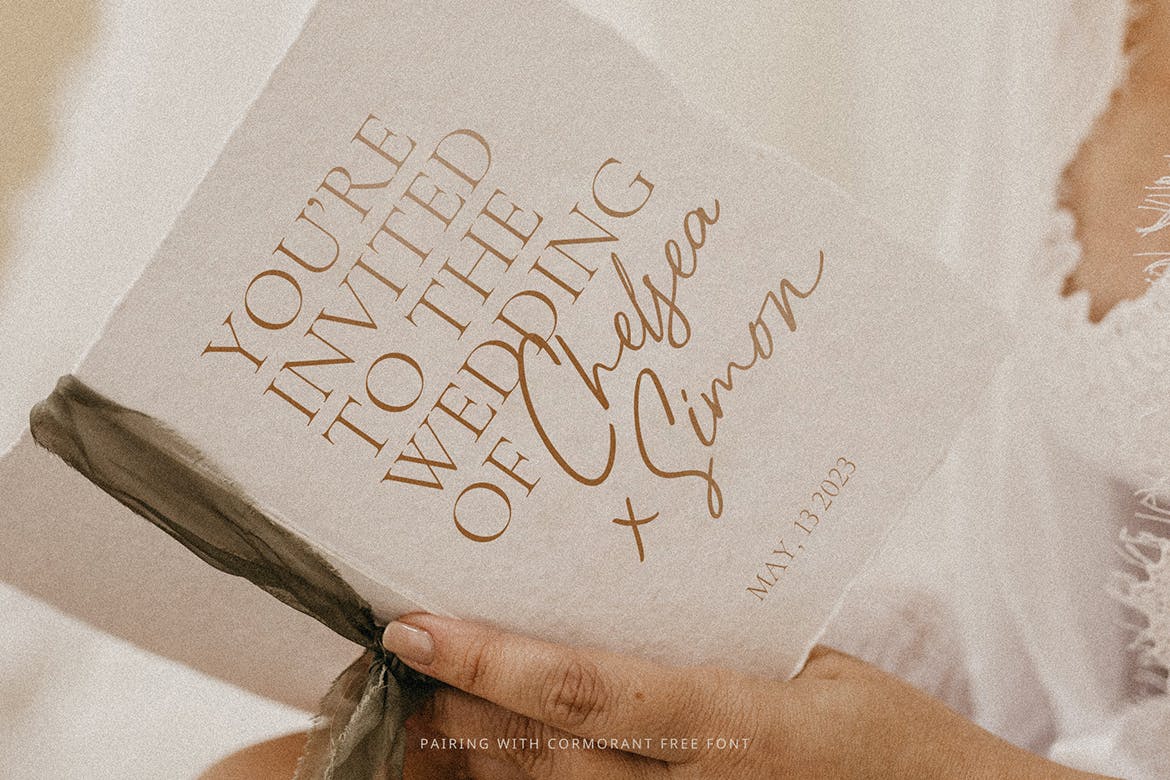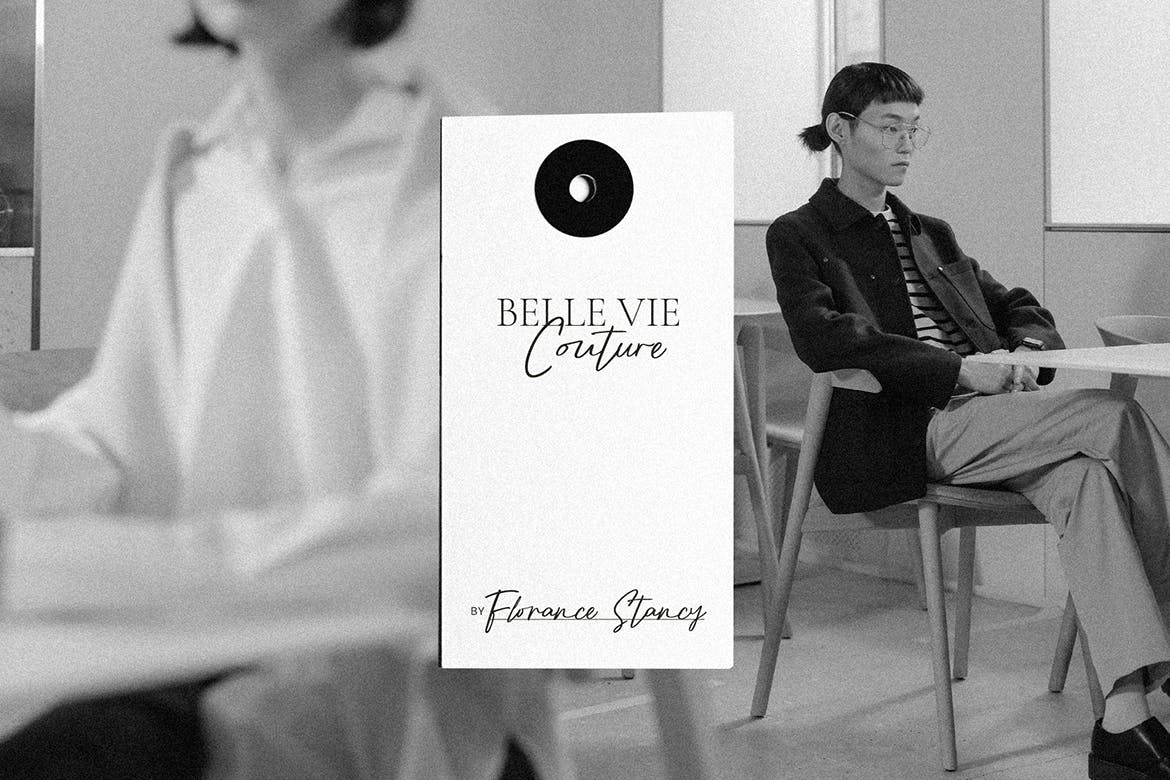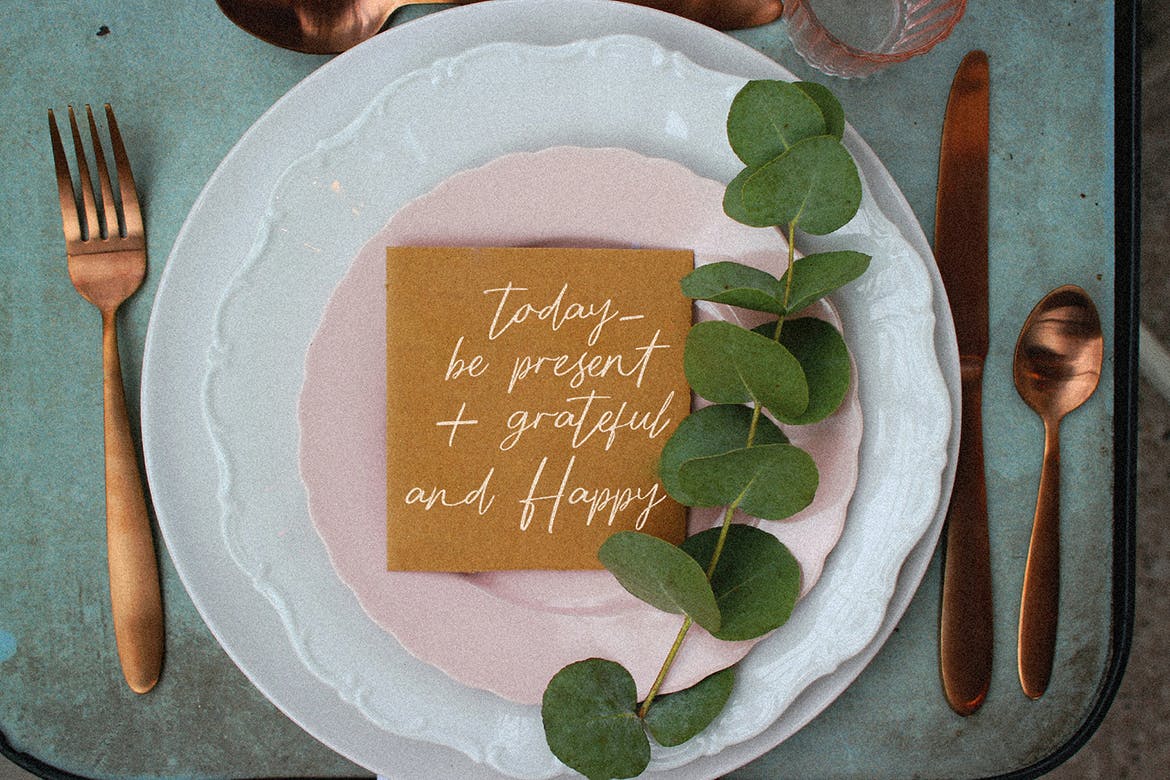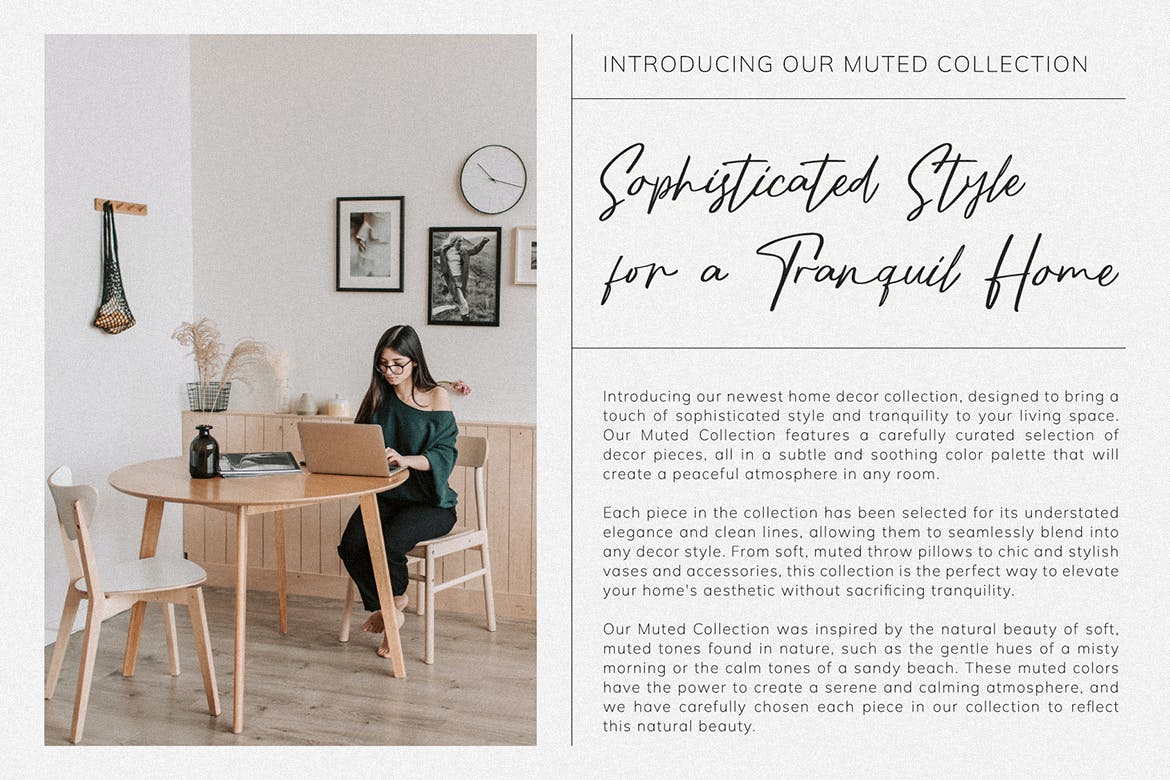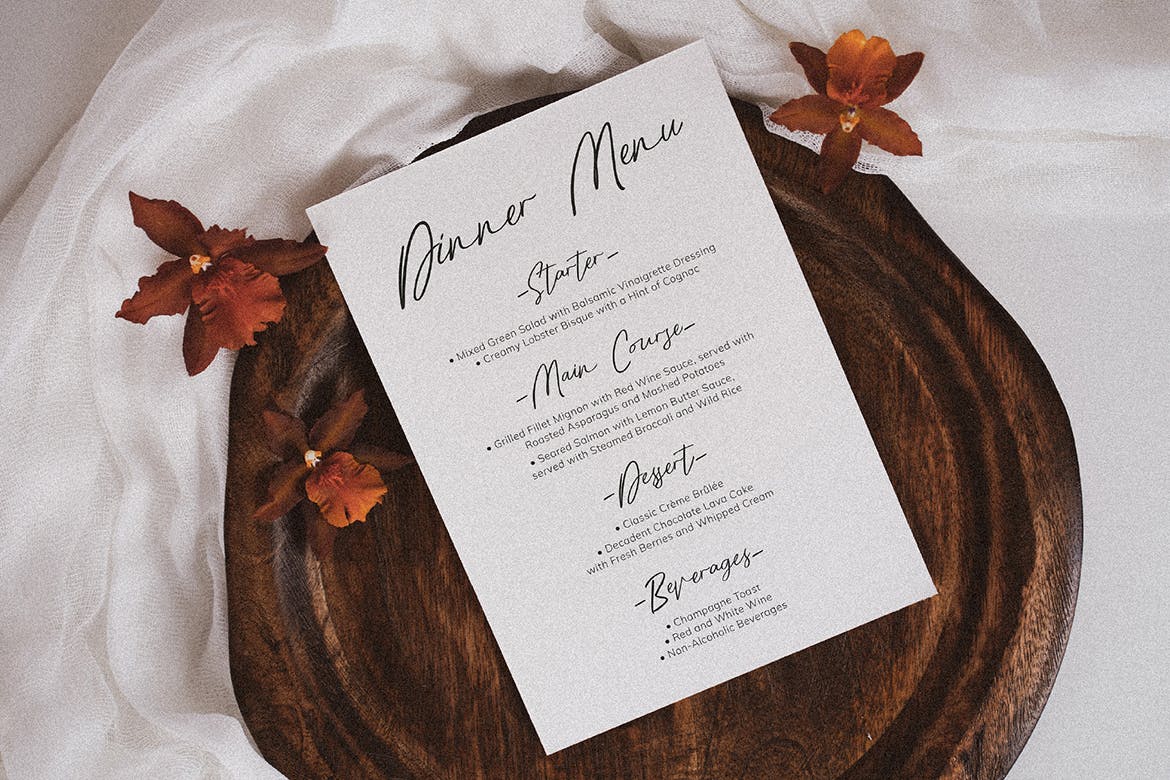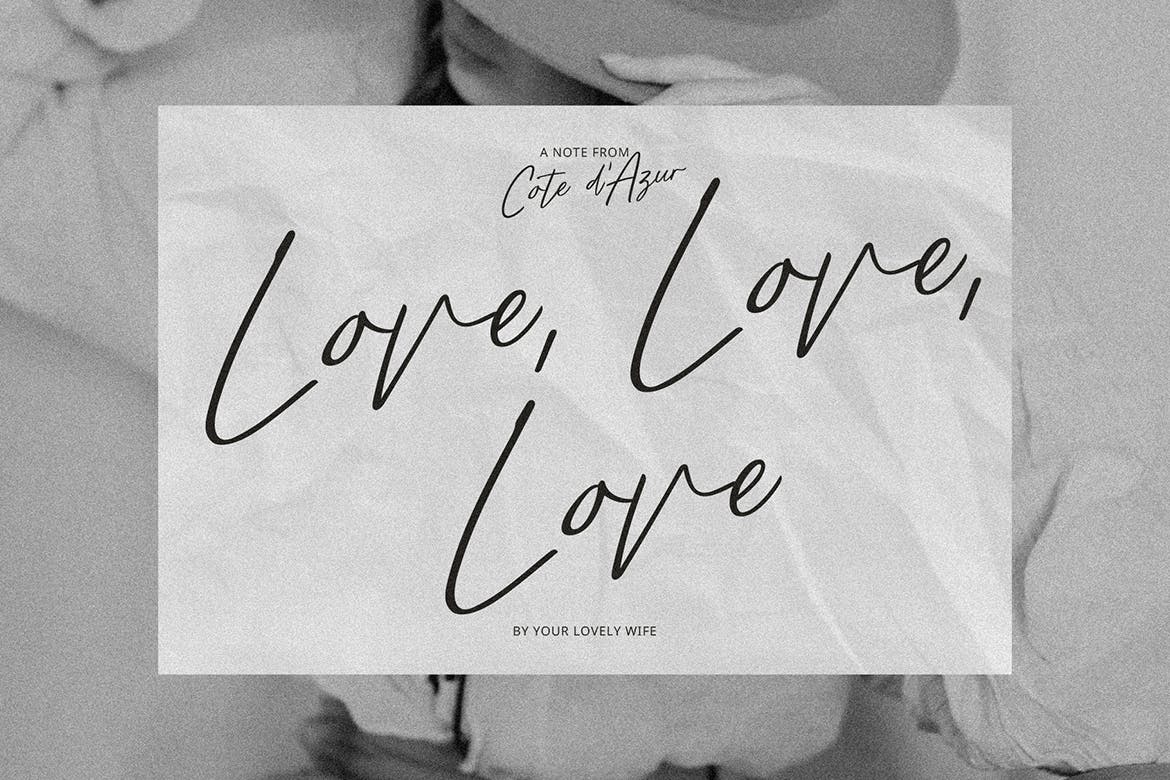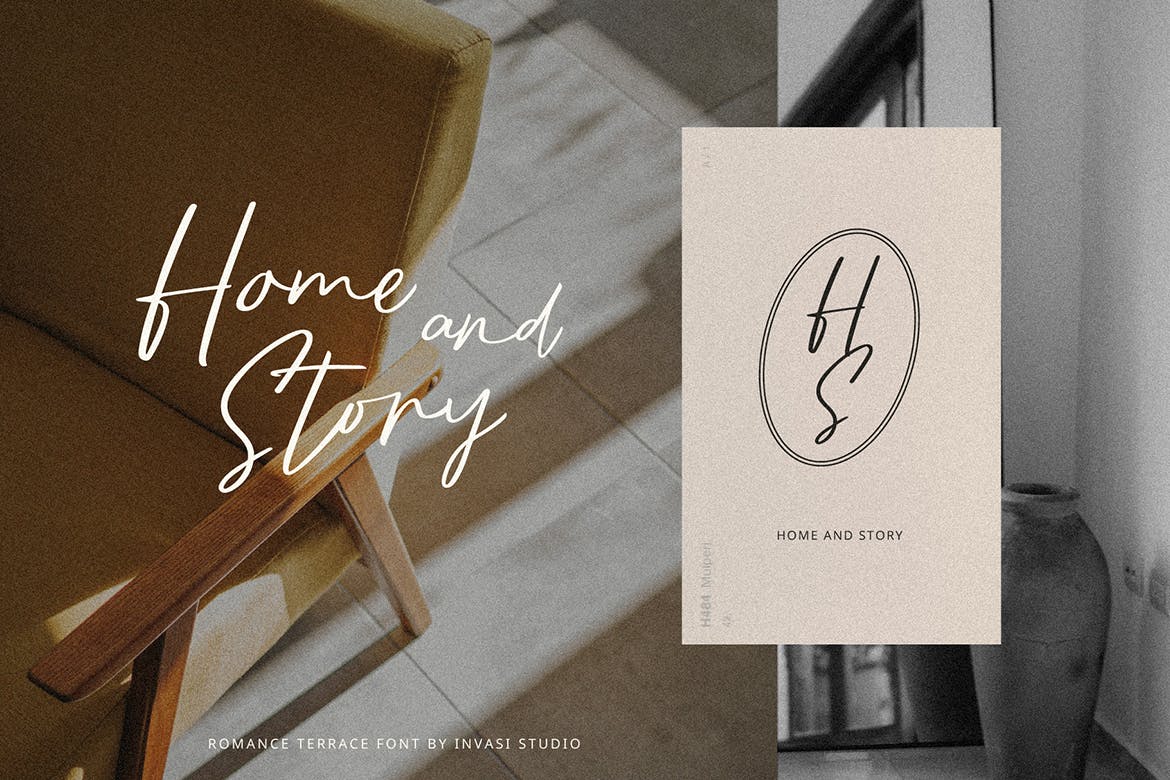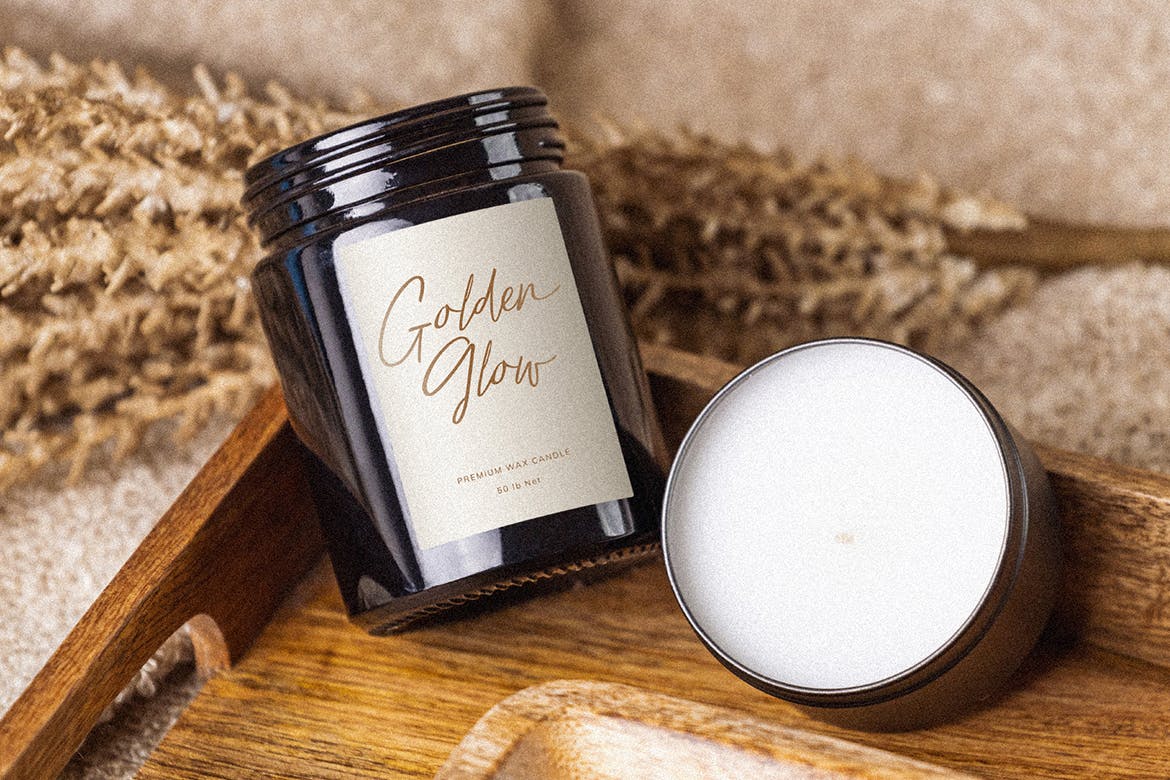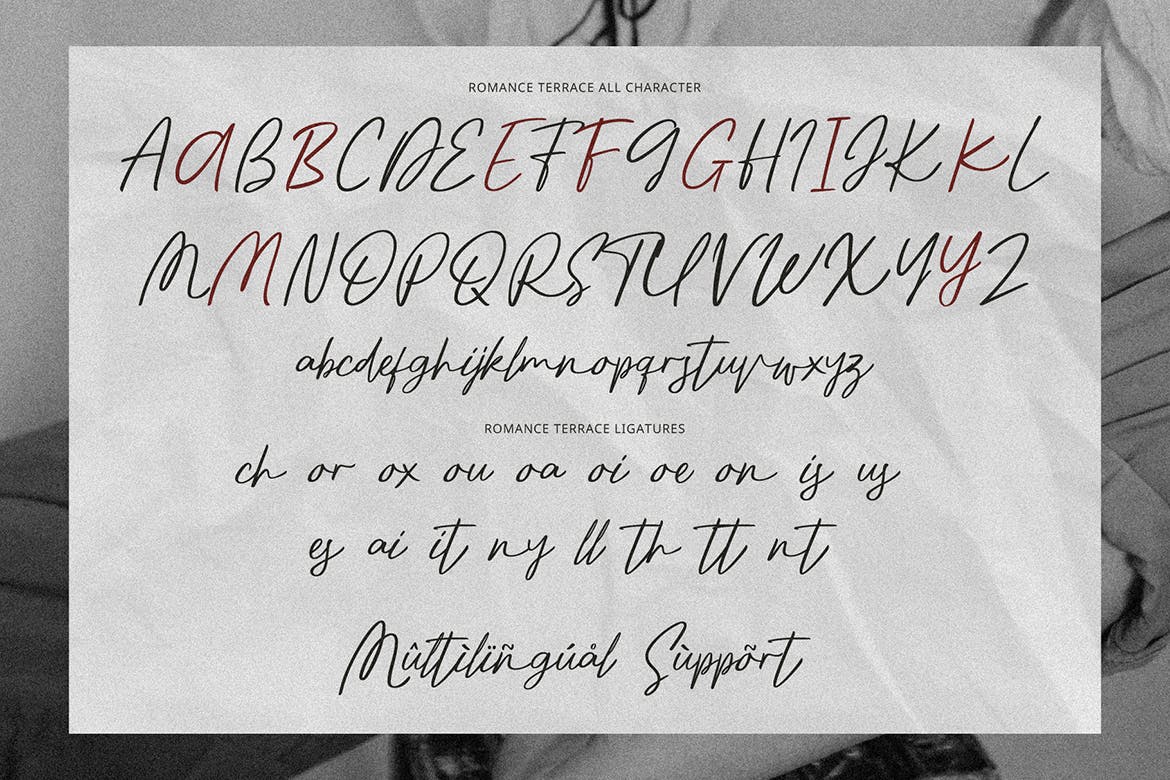
فونت Romance Terrace گزینهای بینظیر برای افزودن لمسهای از لوکس بودن و زیبایی به هر پروژه طراحی است. سبک دستنویس و براش این فونت، حس ظرافت و کلاس را به نمایش میگذارد و آن را برای استفاده در برندینگ، دعوتنامههای عروسی، بستهبندی، منوها و موارد دیگر ایدهآل میسازد.
چه در حال طراحی برای یک برند لوکس و باکیفیت باشید و چه بخواهید لمسهای از جذابیت به پروژه شخصی خود اضافه کنید، Romance Terrace انتخابی کامل است. طراحی کلاسیک و بیزمان این فونت مطمئناً شما را تحت تأثیر قرار خواهد داد و ویژگیهای متعدد آن استفاده و شخصیسازی آن را آسان میکند.